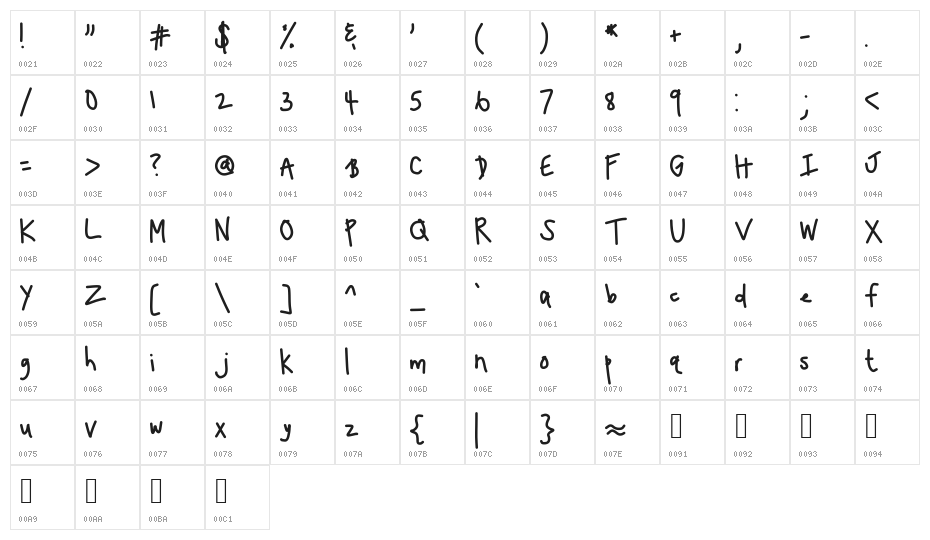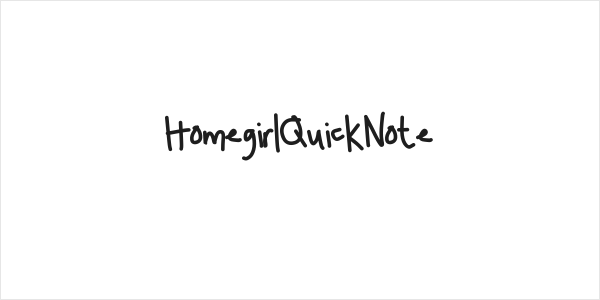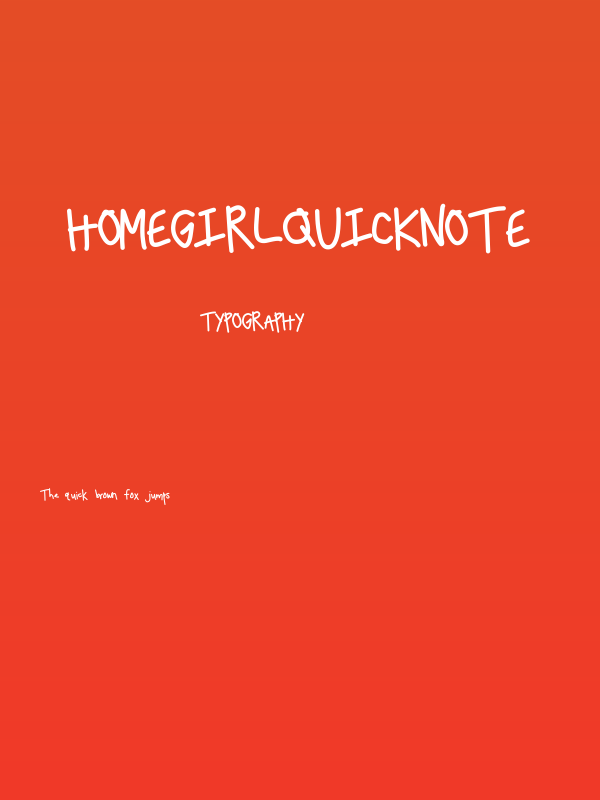
HomegirlQuickNote Font
| Stile generale | Casual, Playful |
| Caso d'uso | Personal notes, Creative projects |
| Progetti proposti | Ideal for personal notes, casual invitations, children's books, and creative projects that require a friendly touch. |